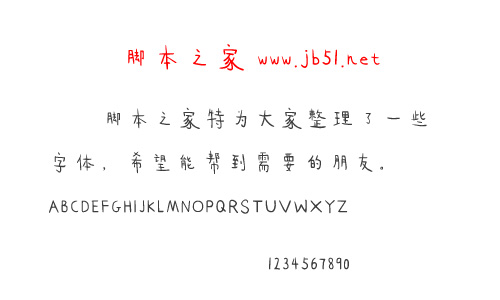
方正寂地體字體是方正字體庫(kù)中的一種字體,方正寂地體由漫畫家寂地創(chuàng)作。這款字體的筆畫從容隨意,字形柔軟單純,字面大小有差異,排成短語(yǔ)后呈現(xiàn)出一定節(jié)奏起伏。方正寂地體帶有一種漫不經(jīng)心的情緒,適用于兒童類的書(shū)刊、品牌廣告和產(chǎn)品包裝設(shè)計(jì),以及社交網(wǎng)絡(luò)的個(gè)性化用字。喜歡的朋友們可以前來(lái)下載使用。